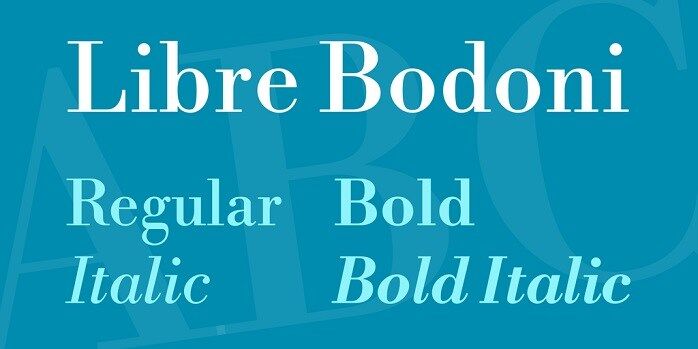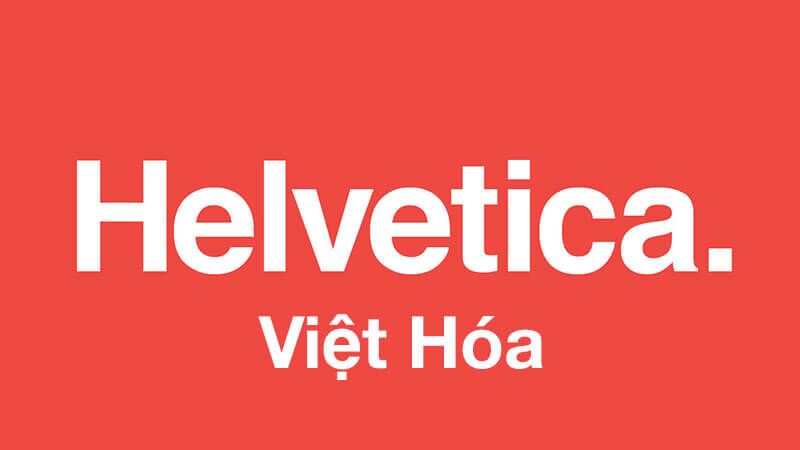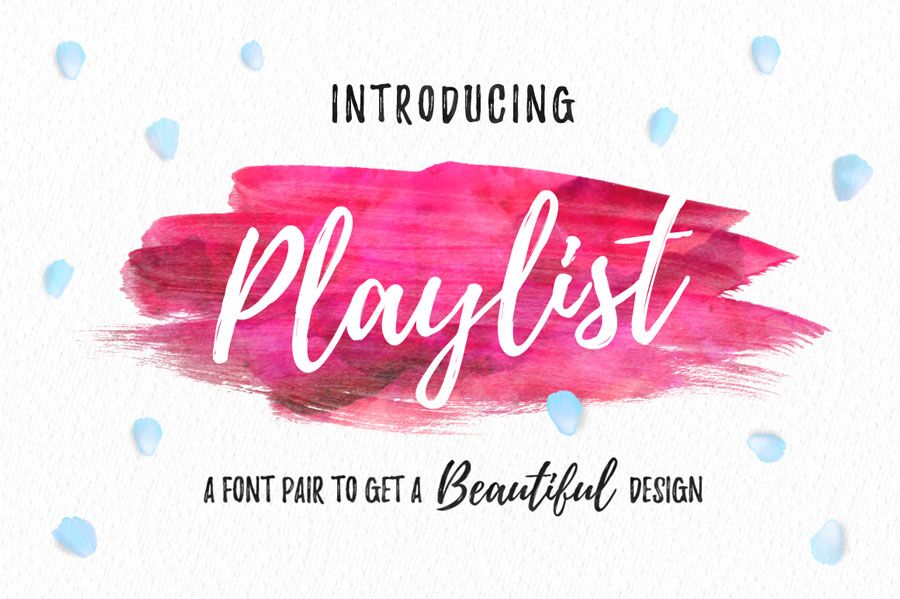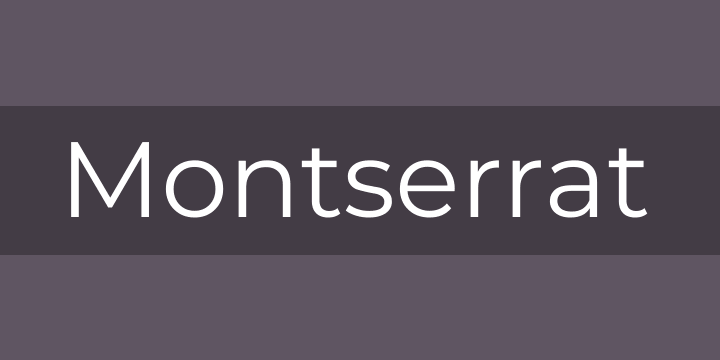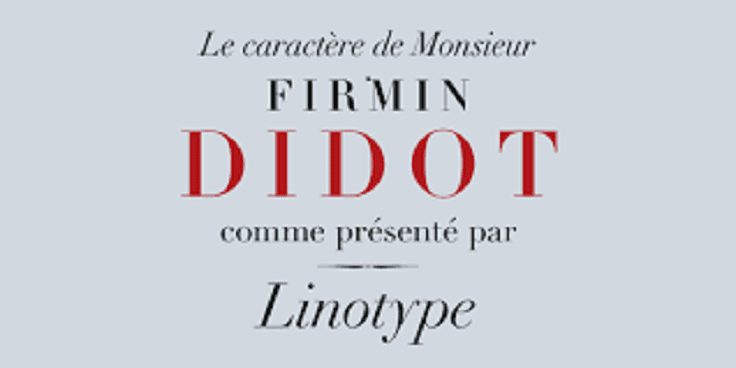
Có rất nhiều bộ font chữ đẹp dành cho photoshop giúp bức ảnh trở lên lung linh và hấp dẫn hơn. Là một designer thì không thể thiếu trong tay bộ font chữ đẹp dành riêng cho photoshop.
Khi chỉnh sửa trên photoshop thì chúng ta không thể không sử dụng đến các font chữ để tạo ra sự nghệ thuật cho bức ảnh, nếu như thiếu đi font chữ sẽ khiến cho tác phẩm của bạn trở nên nhàm chán hơn, không mang đến sức hấp dẫn.
Và nếu như bạn đang muốn tìm kiếm những font chữ đẹp dành cho photoshop với những kiểu dáng, hoa văn bắt mắt để phục cho công việc thiết kế của mình thì bạn không thể bỏ qua bộ font chữ việt hóa cho photoshop mà toonies muốn gửi bạn qua bài viết dưới đây.
FONT CHỮ ĐẸP CHO PHOTOSHOP
TẠI SAO NÊN SỬ DỤNG FONT CHỮ ĐẸP CHO PHOTOSHOP
Nếu như bạn là một nhà thiết kế hay một thợ chỉnh sửa ảnh chuyên nghiệp thì chắc chắn những bộ font chữ căn bản như Unicode, VNI hay UTM,… trong photoshop sẽ không thể khiến bạn ưng ý và cứ dùng mãi từ sản phẩm này đến sản phẩm khác mà không hề có sự đổi mới thì nó sẽ khiến bạn dần trở nên lạc hậu.
Nó không những làm cho sản phẩm thiết kế của bạn trở nên nhạt nhoà vẫn chưa có điểm nhấn mà còn thể hiện sự thiếu chuyên nghiệp và sức thông minh của bạn trong lĩnh vực này. Vì lẽ đó việc thiết lập và cập nhật những font chữ đẹp dành cho photoshop là điều cần thiết và rất quan trọng để tạo sự khác biệt cho các sản phẩm của bạn.
TOP FONT CHỮ CHO PHOTOSHOP SIÊU ĐẸP
Helvetica
Montserrat
Montserrat được thiết kế bởi nhà thiết kế type của Argentina Julieta Ulyanovsky. Thiết kế chữ được lấy cảm hứng từ những bảng biển chỉ dẫn ở Bueno Aires, nơi cô sống.
Đây là bộ font được thiết kế bởi nhà thiết kế type của người Argentina. Đây là font chữ đẹp dành cho photoshop có đường nét đơn giản dễ đọc, rất phù hợp cho thiết kế banner, thông báo… Đây cũng là bộ font chữ rất được ưa chuộng của các thiết kế.
Montserrat có tất cả 8 kiểu, gồm Hairline, Ultra Light, Light, Regular, Semibold, Bold, Extra Bold và Black. Những tính năng opentype và kerning đều đã được iCiel trau chuốt tỉ mỉ. Tuy nhiên vì độ đậm của font chữ đẹp này mà nó sẽ là con dao hai lưỡi khi mà bạn dùng nó để trình bày những đoạn văn dài đấy.
Garamond
Là một font chữ đẹp chuyên dành cho tạp chí,sách, web và những văn bản nhiều nội dung vì các nghiên cứu cho rằng nó rất dễ đọc với mắt.
Có rất nhiều phiên bản cho Garamond, phiên bản được sử dụng nhiều nhất là Adobe Garamond, được phát hành năm 1989.
Garamond có dáng vẻ thanh lịch. Các chân chữ trên mỗi kí tự được làm thủ công cẩn thận để truyền đạt tính cách của nó, đáng chú ý nhất là ký tự viết hoa “T”. Bởi vì chân chữ mỗi ký tự rất biểu cảm, chúng đã được sử dụng trong một bối cảnh vui tươi như trong thương hiệu Apple những năm đầu tiên.
Beautiful Bloom
Đây là một bộ font chữ đẹp cho photoshop được kết hợp hoàn hảo của cả 2 loại là font chữ viết tay hoặc những font chữ theo phong cách thư pháp được xác thực với đầy đủ các thay thế (chữ hoa và chữ thường).Beautiful Bloom được thiết kế để hoạt động hoàn hảo trong nhiều kiểu dáng như thiệp mời đám cưới, biểu trưng trang web, bài đăng trên Instagram và nhiều hơn nữa.
Linotte
Linotte là một font chữ đẹp photoshop được thiết kế bởi Joël Carrouché. Những điểm nhấn nhỏ tạo cho font chữ một cái nhìn ấm áp và ngây thơ, trong khi cấu trúc hình học vững chắc cho phép dễ đọc trong các văn bản dài và kích thước nhỏ.
Linotte thật là lý tưởng dùng để thiết kế cho các sản phẩm thực phẩm hoặc có liên quan trẻ em hay bất cứ điều gì cần phải chuyển tải một cảm giác thân thiện.
Playlist
Playlist là bộ font viết tay theo phong cách brush, bao gồm 3 style: Script, Caps và Ornament giúp bạn tùy biến cho tác phẩm thiết kế của mình hoàn hảo nhất. Font chữ hỗ trợ đầy đủ bộ ký tự cơ bản, có thêm font Ornament hỗ trợ các ký tự hoa văn trang trí.
Tác giả Artimasa cung cấp miễn phí font này có thể được sử dụng trong bất kỳ mục đích nào cá nhân và thương mại. Font chữ phù hợp với thiệp đám cưới, thiệp chúc mừng, hình minh hoạ, trích dẫn, áp phích, thiết kế áo thun .
Futura
Futura có thể là một trong những font chữ thành công và được sử dụng nhiều nhất trong thế kỷ 20. Các mẫu chữ hình học bất quy tắc này thể hiện một chủ nghĩa hiện đại lạc quan. Font chữ Futura hiện nay đã trở thành một trong những font chữ đẹp được dùng trong photoshop rất phổ biến khi được nhiều nhà thiết kế sử dụng trong logo, sản phẩm thương mại quảng cáo.
Bodoni
Kiểu chữ Bodoni nổi lên trong thời gian khi các nhà thiết kế chữ đang thử nghiệm sự tương phản giữa độ dày mỏng của các kí tự. Giambattista Bodoni đã thực hiện thí nghiệm đó một cách khác thường, tạo ra phông chữ ấn tượng này. font chữ đẹp này đã tạo nên thành công vang dội qua các biểu tượng nổi tiếng như Vogue và Calvin Klein, và là một typeface tuyệt vời để sử dụng cho các thương hiệu thời trang chính thống.
Bodoni là sự lựa chọn tuyệt vời nếu bạn muốn tìm một font chữ cho tiêu đề hay logo của mình. Bodoni có cấu trúc cơ bản hẹp với các serif thẳng và mảnh. Bề mặt font chữ photoshop này có độ tương phản cao giữa các nét thanh và nét đậm khiến nó mang tính thẩm mỹ cao hơn trong thiết kế.
KẾT LUẬN